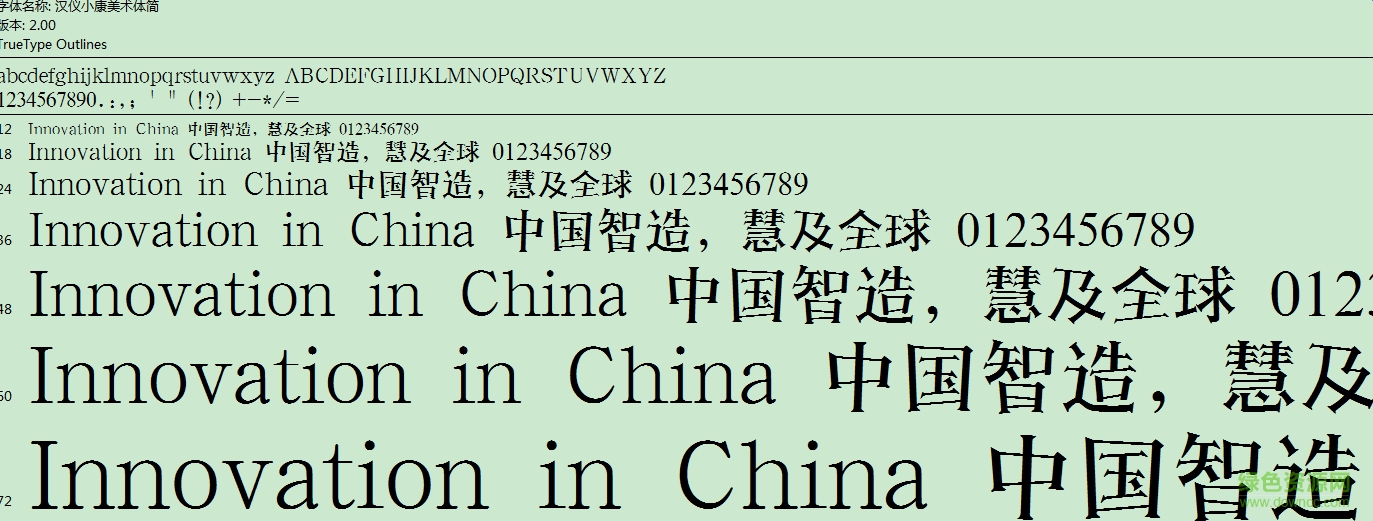
漢儀小康美術(shù)體簡(jiǎn)
漢儀小康美術(shù)體簡(jiǎn)字體是一款漢儀出品的簡(jiǎn)體字體,用途廣泛,美工設(shè)計(jì)、廣告海報(bào)設(shè)計(jì)等方面都可以使用,小編為大家?guī)?lái)免費(fèi)下載地址,歡迎大家來(lái)綠色資源網(wǎng)踴躍下載哦!
漢儀小康美術(shù)體簡(jiǎn)字體
漢儀小康美術(shù)體簡(jiǎn),一款看起來(lái)并不規(guī)則的藝術(shù)字體,字體整體結(jié)構(gòu)緊湊,既工整又大氣。